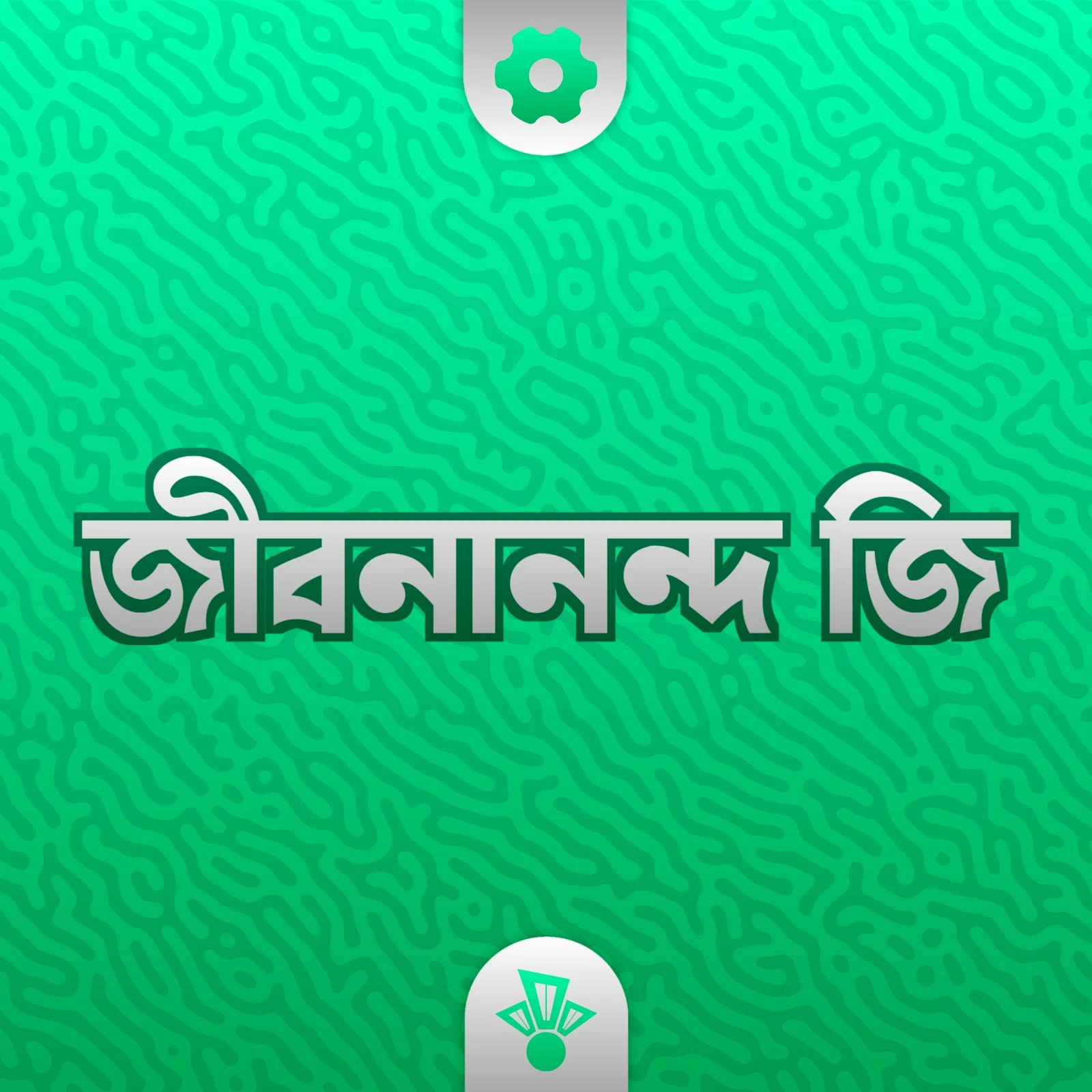
জীবনানন্দ জি একটি ইউনিক বোল্ড স্টাইলের প্যারাগ্রাফ বাংলা ফন্ট। এটি মূলত একটি কর্পোরেট ফন্ট এবং শুধুমাত্র মালিকপক্ষেরই এটি ব্যবহারের অনুমতি রয়েছে
জীবনানন্দ জি
- নকশাকার : গবিন্দ মজুমদার
- বিকাশকারী : গবিন্দ মজুমদার